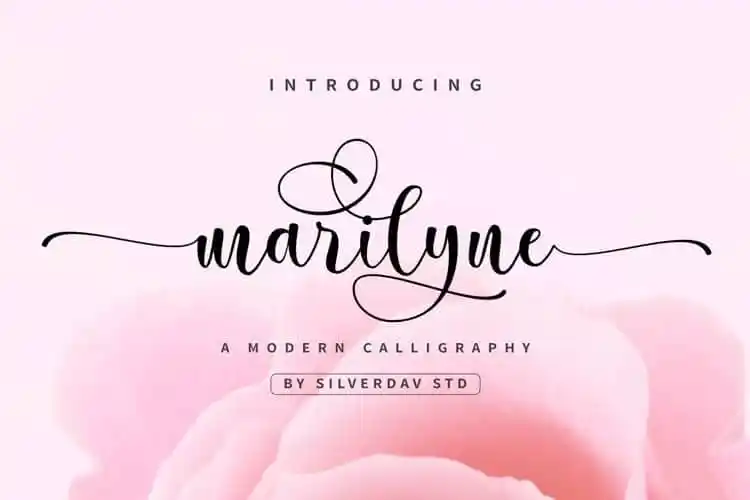
Marilyne Calligraphy Font
A fonte “Marilyne Calligraphy Font” é uma escolha ideal para quem busca adicionar um toque elegante a seus projetos digitais, seja eles websites, logotipos ou materiais de marketing. Com seu estilo moderno e fluidez chamada, cada letra é cuidadosamente personalizada para melhorar ainda mais a qualidade dos teus designs. Silverdav criou este font bold e conectado, perfeito tanto para as necessidades da marca como para os recados românticos do casamento. Com seu coração palpável e um universo de símbolos, esta font é ideal para criar identidade visual moderna, sejam eles cartões de agradecimento ou anúncios de casamento. Ela destaca-se com sua sofisticação, criando ambientes que transmitem elegância e harmonia, tornando-a uma excelente opção para qualquer projeto que precise de um toque personalizado e sofisticado.